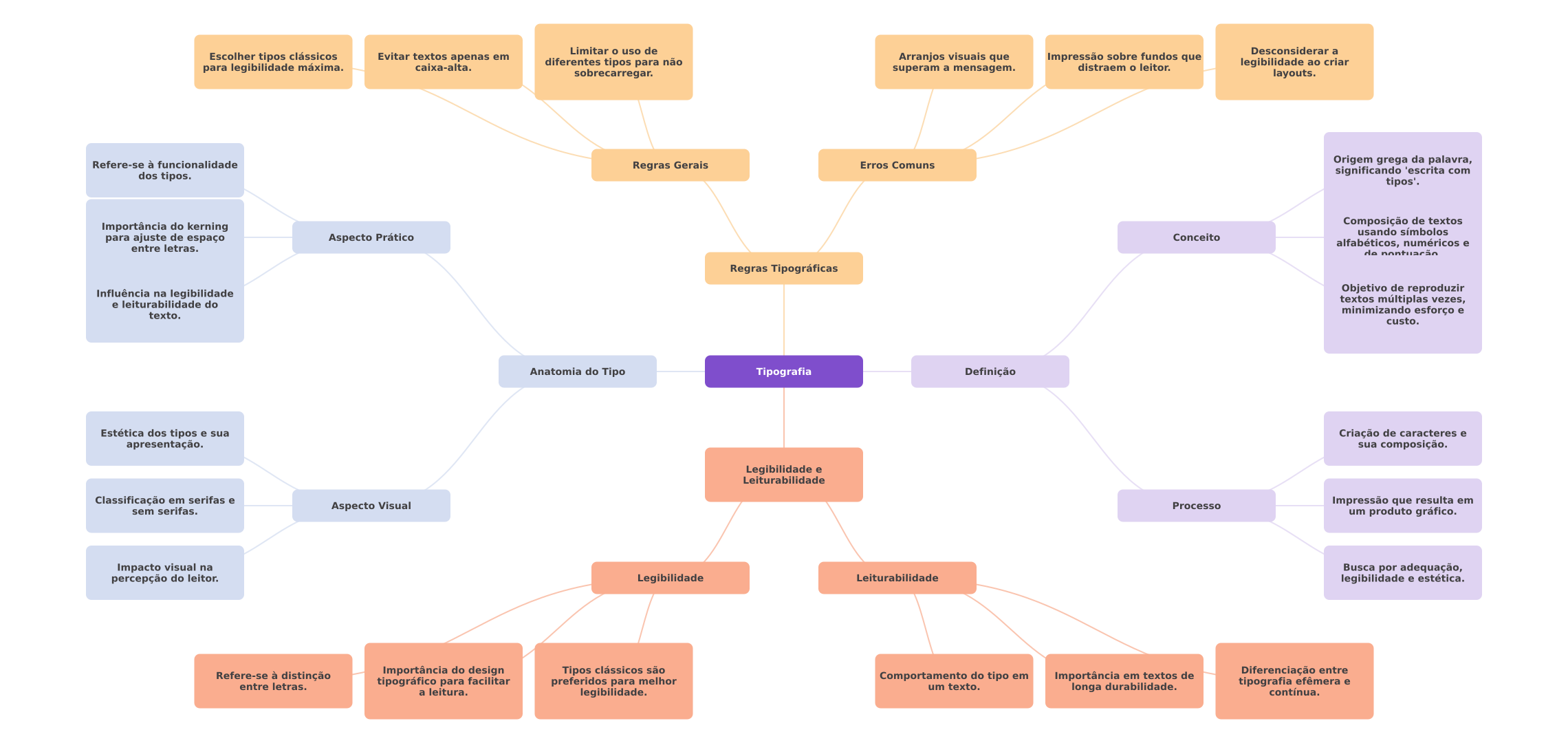
Limitar uso de Desconsiderar a Escolher tipos clássicos Evitar textos apenas em Arranjos visuais que Impressão sobre fundos que para legibilidade máxima. caixa-alta. diferentes tipos para não distraem leitor. legibilidade ao criar sobrecarregar. superam a mensagem. layouts. Origem grega da palavra, Refere-se à funcionalidade Regras Gerais Erros Comuns significando 'escrita com dos tipos. tipos'. Composição de textos Importância do kerning usando símbolos para ajuste de espaço Aspecto Prático Conceito alfabéticos, numéricos e entre letras. de Regras Tipográficas Objetivo de reproduzir Influência na legibilidade e leiturabilidade do textos múltiplas vezes, minimizando esforço e texto. custo. Anatomia do Tipo Tipografia Definição Estética dos tipos e sua Criação de caracteres e apresentação. sua composição. Legibilidade e Leiturabilidade Classificação em serifas e Aspecto Visual Processo Impressão que resulta em sem serifas. um produto gráfico. Impacto visual na Busca por adequação, percepção do leitor. Legibilidade Leiturabilidade legibilidade e estética. Refere-se à distinção Importância do design Tipos clássicos são Importância em textos de Diferenciação entre entre letras. tipográfico para facilitar preferidos para melhor Comportamento do tipo em um texto. a leitura. legibilidade. longa durabilidade. tipografia efêmera e contínua.